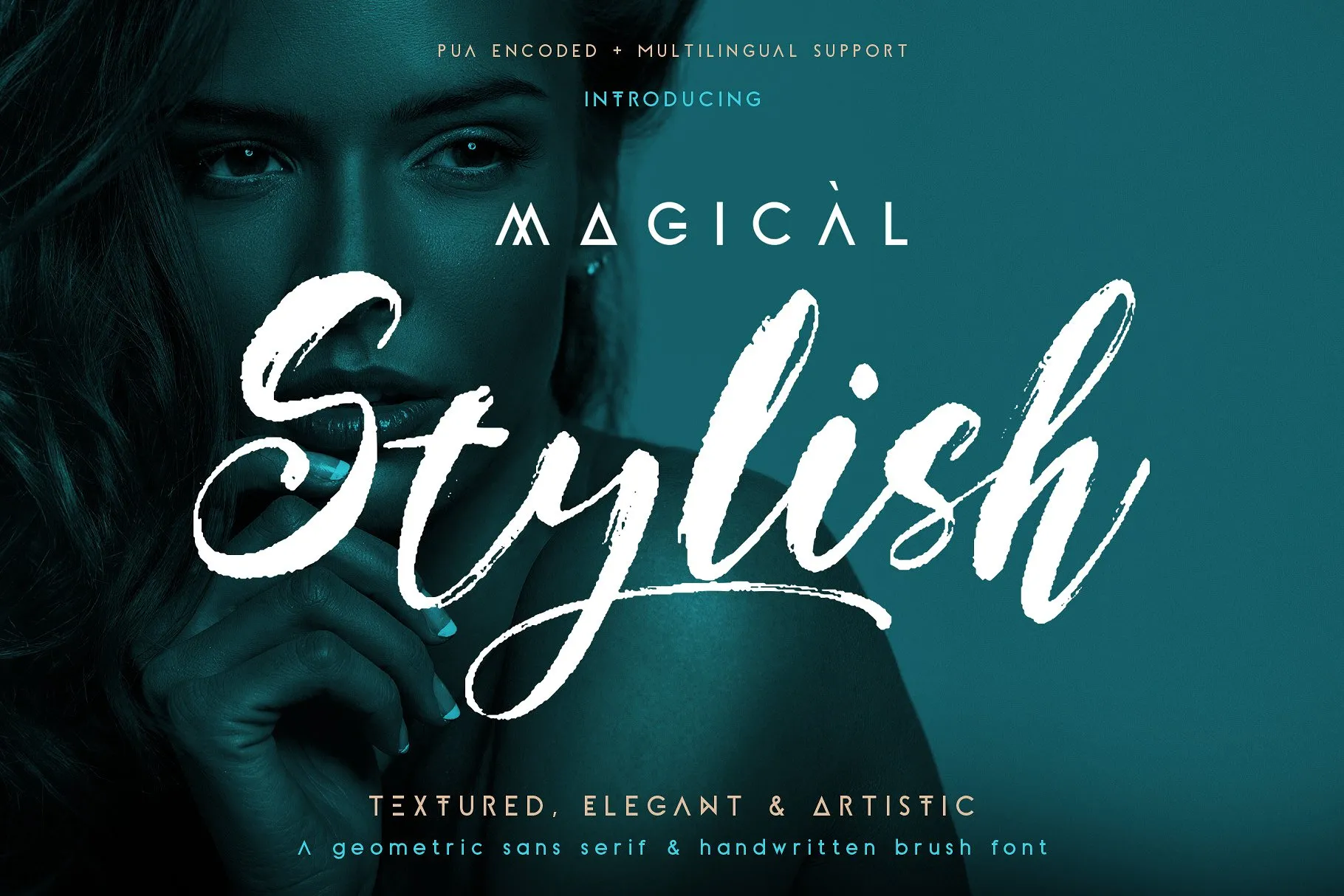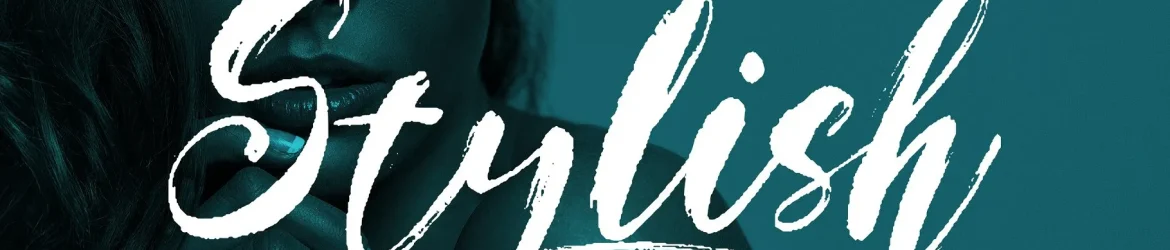
Magical Stylish – Font Duo – Download Grátis
Aqui está uma versão adaptada dos parágrafos curtos para a descrição do download da font ‘Magical Stylish – Font Duo’: Embalada com a versatilidade de um tipo geométrico e um estilo fluido feito à mão, o Magical Stylish é uma combinação perfeita de modernidade e personalização. Esta seleção única inclui dois tipos: um sans serif geometricamente refinado e outro em estilos brush que imprimem um ar suave e despojado às suas criações digitais. Com a facilidade de uso que promete a cada toque, basta digitar ou copiar e colar o texto que deseja aplicar. Assim que você pressiona enter, as palavras transformam-se numa arte à medida do seu gosto. O fechamento do MagicStylish vem com um conjunto alternativo de letras maiúsculas para garantir a aparência desejada. A Magical Stylish é uma escolha perfeita para aqueles que buscam expressar personalidade e sofisticação através do design digital. Composta por elementos geométricos e grafismos fluidos, este tipo oferece flexibilidade para criar designs diversos, desde rótulos elegantes até peças de escrita informal.